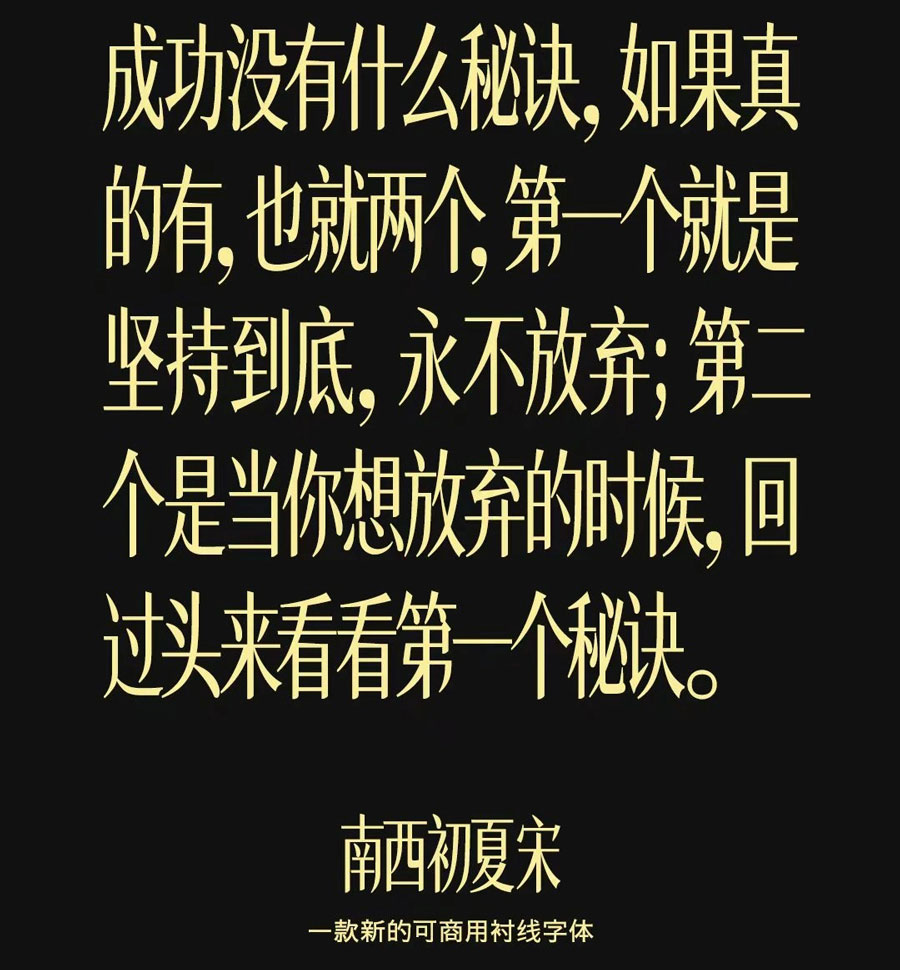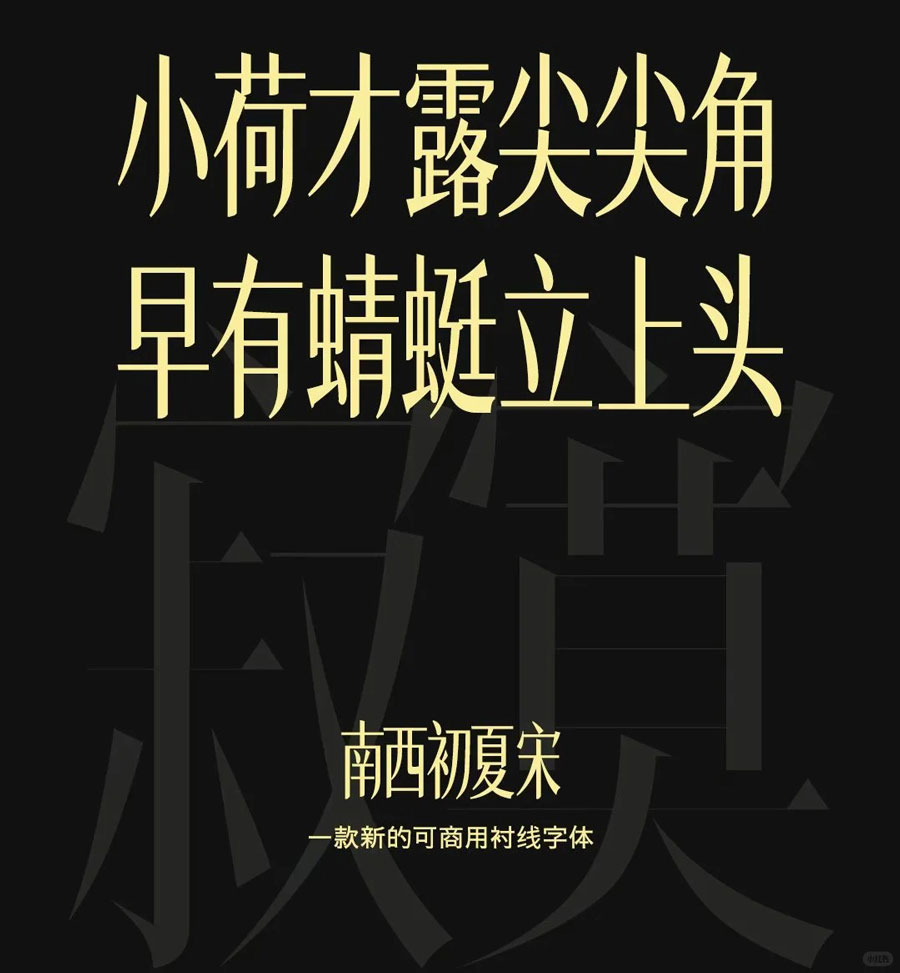
南西初夏宋是由小红书博主@松陵南西 基于思源宋体二次改造的一款免费可商用中文衬线字体。设计师在保留传统宋体“横细竖粗”特点的基础上对字形笔画末端进行了改造,增加了微微上扬的弧度,撇捺更舒展飘逸,既有手写的灵动又兼具衬线的精致,削弱了传统宋体的庄重感。
字符集覆盖 GB2312(6763 常用简体字),繁体也基本全兼容,总字符数达 10097 个,满足不同场景的中文排版需求。比如小红书/公众号等社交媒体的图文标题、品牌文艺风 Slogan、海报、文创排版等;尤其适合清新、文艺、生活类主题;但不推荐小字号的密集正文以及科技感强的设计场景。